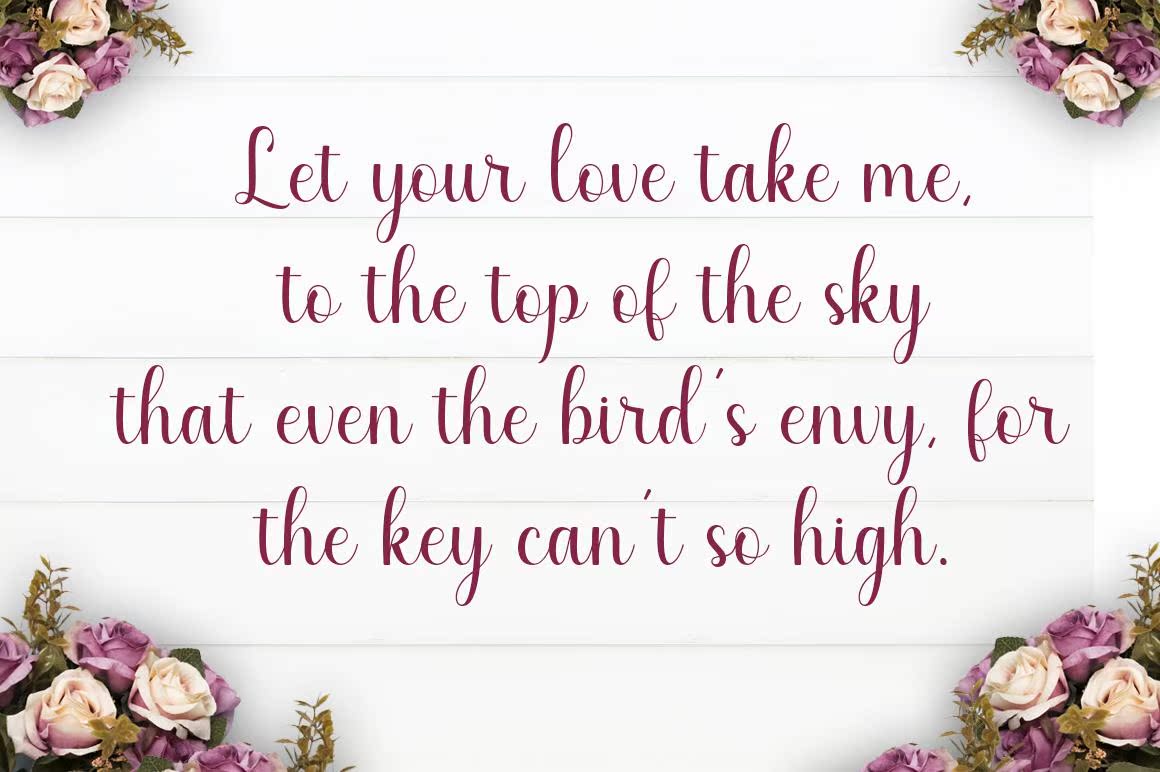
Cherilyn在运行影响范围内启用了一个具有iquiefeeland的全光手写字体。它将添加您希望创建的任何设计项目!这是一种编码方式,表示您可以使用此编码方式和连字开关!Cherilyn在运行影响范围内启用了一个具有iquiefeeland的全光手写字体。它将添加您希望创建的任何设计项目!这是一种编码方式,表示您可以使用此编码方式和连字开关!